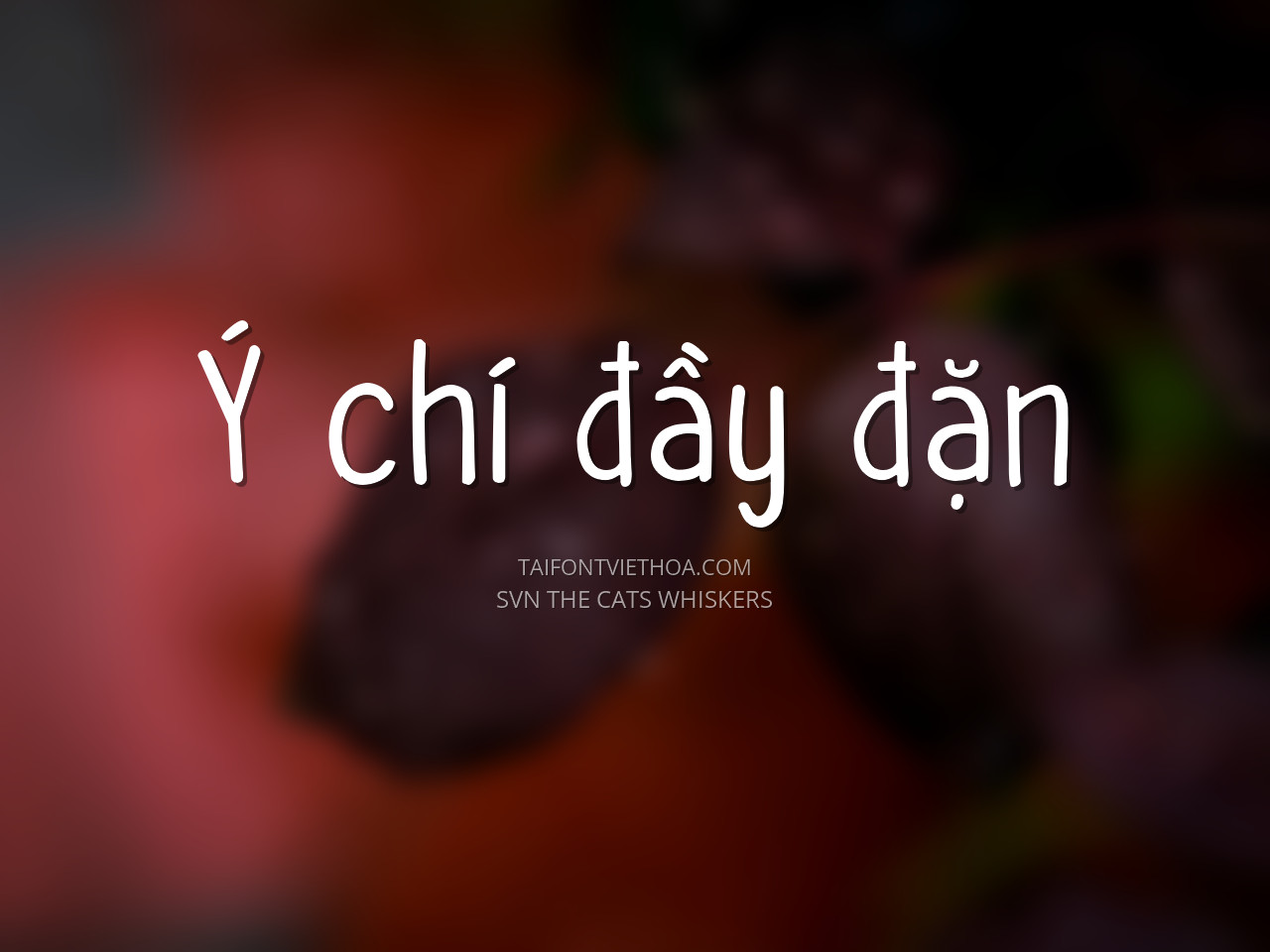
Font việt hóa SVN The Cat Whiskers
Tác giả Font: David Kerkhoff
Giới thiệu về The Cat Whiskers – Font handwritten dễ thương, vui nhộn và cá tính
The Cat Whiskers (tên gốc: The Cat Whiskers Typeface) là phông chữ viết tay (handwritten) độc đáo được phát triển bởi Rivka’s Art(Indonesia) và ra mắt lần đầu trên Creative Market năm 2020. Lấy cảm hứng từ những nét bút tay tự nhiên pha chút tinh nghịch và mềm mại, The Cat Whiskers gây ấn tượng bởi kiểu dáng tròn trịa, đáng yêu, cực kỳ phù hợp với các thiết kế dành cho trẻ em, thương hiệu sáng tạo, sản phẩm handmade hoặc những dự án cần tạo sự gần gũi, vui nhộn. Phiên bản quốc tế hỗ trợ trên 60 ngôn ngữ Latincùng bộ ký tự đặc biệt, số, alternates và ligatures, giúp font dễ dàng ứng dụng cho nhiều mục đích thiết kế khác nhau.
Đặc điểm thiết kế, ứng dụng và ngành nghề phù hợp
The Cat Whiskers thuộc nhóm viết tay (handwritten), sở hữu đường nét tròn trịa, mềm mại, các ký tự được thiết kế ngộ nghĩnh với những điểm nhấn tinh tế tạo nên cảm giác thân thiện, gần gũi. Bộ alternates và ligatures phong phú giúp cá nhân hóa tiêu đề, poster hoặc các sản phẩm handmade. Font còn cực kỳ hiệu quả khi sử dụng trên bao bì sản phẩm trẻ em, thiệp mời, sổ tay, nhãn mác, sticker hoặc các ấn phẩm truyền thông cần nhấn mạnh yếu tố vui nhộn, đáng yêu.
Ứng dụng tiêu biểu
– Logo & nhận diện:Thương hiệu handmade, shop đồ trẻ em, spa, beauty salon, thương hiệu đồ chơi.
– Ấn phẩm truyền thông:Poster thiếu nhi, sticker, thiệp mời sinh nhật, story social media, banner sáng tạo.
– Bao bì & nhãn mác:Nhãn sản phẩm, hộp quà, sổ tay, sản phẩm thủ công và nghệ thuật.
Ngành nghề phù hợp
The Cat Whiskers là lựa chọn lý tưởng cho ngành quảng cáo, sáng tạo, giáo dục, sản phẩm cho trẻ em, handmade, tổ chức sự kiện, spa & beauty… Khi kết hợp cùng các font sans-serif, The Cat Whiskers sẽ giúp tổng thể thiết kế thêm phần tươi vui, gần gũi và khác biệt. Tải ngay bản Việt hóa tại taifontviethoa.com để trải nghiệm trọn bộ glyph cho mọi dự án thiết kế của bạn.